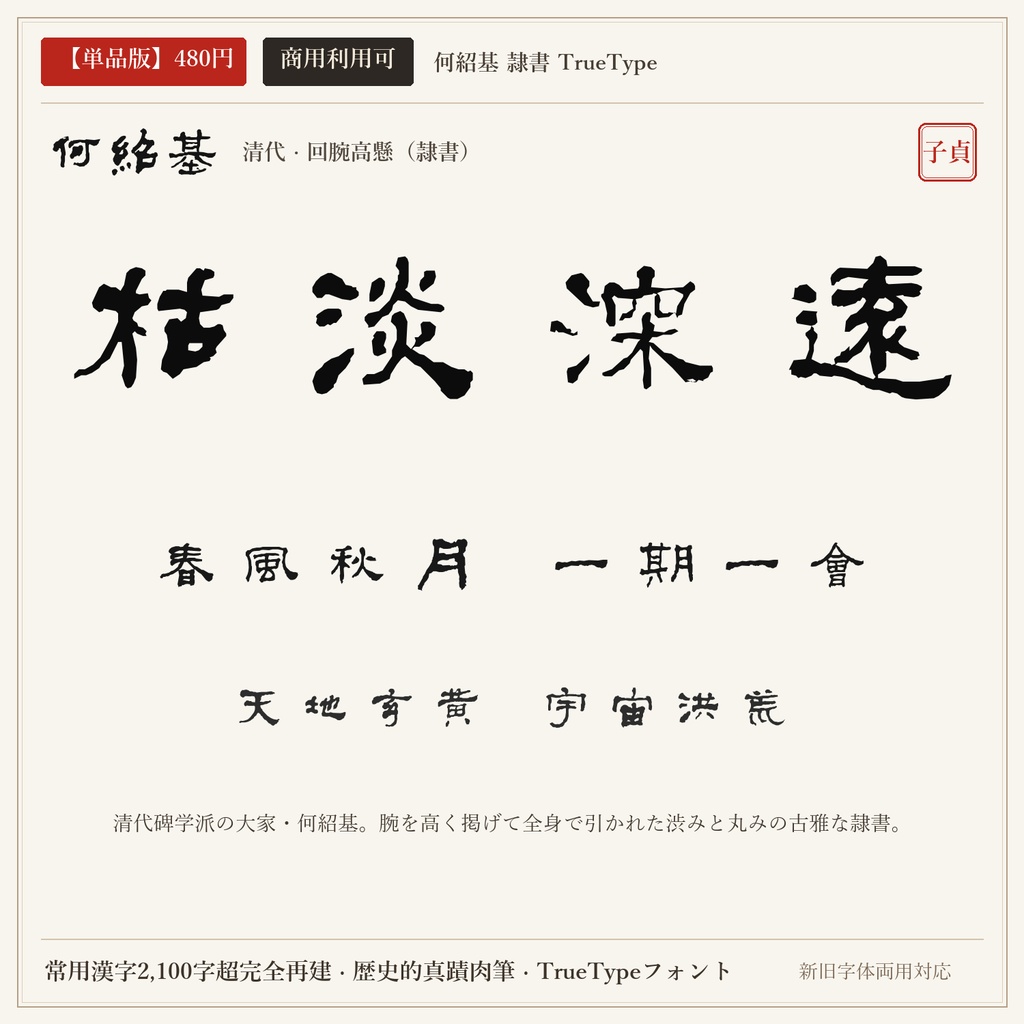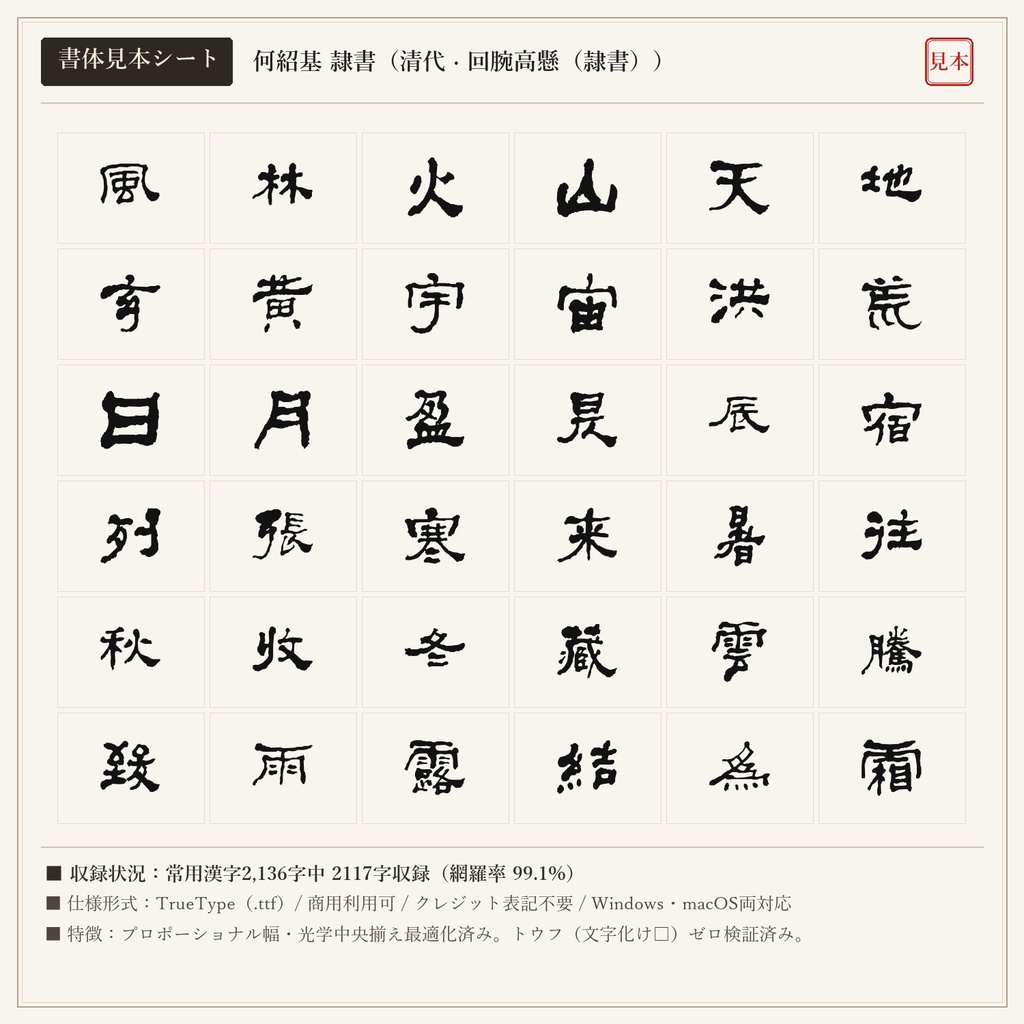
【単品版】何紹基 隷書フォント|回腕高懸・枯淡重厚の極致・商用利用可
清代後半の碑帖兼修の巨匠・何紹基の真蹟隷書から制作されたフォントです。肘を張り腕を高く掲げる「回腕高懸法」によって生み出される、震えるような深みのある線条と円渋な金石美が特徴です。 ■ 本フォントの特徴 ・常用漢字2,136字中、2117字を高精度収録(網羅率 99.1%)。 ・現代の新字体を入力しても、歴史的な真蹟字形・旧字体が自然に出力されるデュアルマッピング対応。 ・文字ごとの最適なプロポーショナル字幅設定により、自然で流麗な連綿と墨の息遣いを再現。 ・トウフ(文字化け□)を出さない事前フォントマッピング検証済み。 ■ 未収録文字一覧(全19字) 歴史的真蹟・拓本に存在しない以下の字種は未収録(非対応)となります。ご購入前にご確認ください。 刹 厘 唄 堀 峠 扱 拶 枠 栃 桁 濫 碁 線 繰 脊 菓 著 込 酎 ■ 形式 TrueTypeフォント(TTF) / Windows・macOS両対応 ■ 利用規約 個人・法人の商用利用OK。クレジット表記不要。 ロゴ、動画、ゲーム、書籍、同人誌、配信サムネイル、Web、印刷物、グッズ等に自由にご使用いただけます。 フォントファイル自体の再配布・共有・販売・転売は禁止です。 ※東晋の王羲之(行書)と盛唐の顔真卿(楷書)を同梱した「【無料版】王羲之 + 顔真卿 2書体セット(0円)」もショップ内にて無料配布中です。